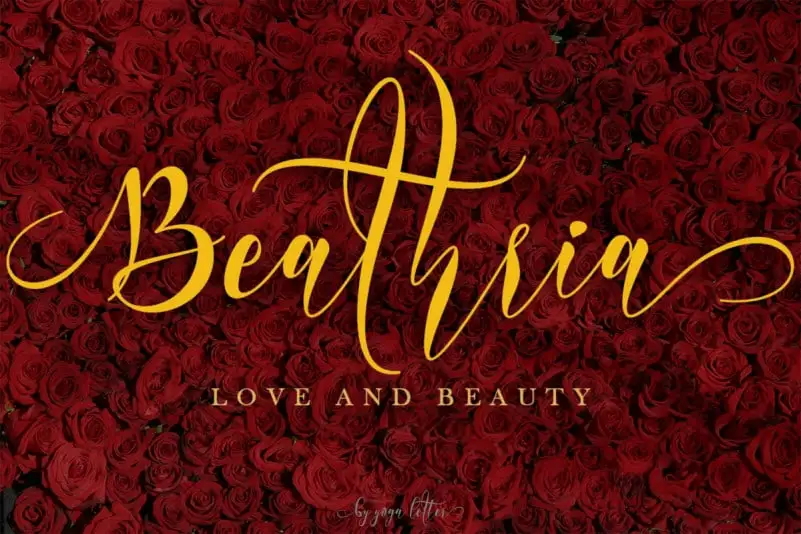
Beathria Calligraphy Font – Download Grátis
Esta fonte é chamada Beathria Calligraphy Font. Ela foi criada com cuidado para oferecer um resultado elevado e elegante. Seu formato delicado resulta em uma fonte de alta qualidade, perfeita para todos os tipos de trabalho. Além disso, esta fonte se destaca em ocasiões especiais como casamentos. É adequada para todas as necessidades relacionadas com o casamento, incluindo convites para casamentos, fotografias de casamentos, decorações e designs para eventos casamenteiros. Além disso, é perfeita para promover seu negócio – hotéis, vilas, lugares de descanso turístico ou qualquer produto e serviço que você tenha a oferecer. Além disso, essa fonte também se adequa a atualizações de promoção, logotipos, marcações, panfletos ou até mesmo as suas publicações em redes sociais. A Beathria Calligraphy Font é uma ótima opção para qualquer projeto que esteja procurando um toque elegante e sofisticado.